Typography là gì? Những quy tắc thiết kế font chữ trong typography
Typography là gì?
Typography là tất cả những gì bạn có thể đọc được nó. Typography được viết tắt là Typo. Nó Hiển thị ở khắp mọi nơi như những trang web, sách báo, hay là cả những ngôn từ hiển thị ở cả những dãy phố ven đường. Trong thiết kế người ta sử dụng Typography để tạo ra những phong cách thiết kế khác lạ. Typography sử dụng để nâng tầm trong thiết kế. Bạn có thể xem những bức ảnh dưới đây thì sẽ hình dung được Typography áp dụng được vào thực tế.
Với 1 số Typography đẹp thì chúng được làm rất là kỳ công và mất nhiều thao tác như bức hình dưới đây
Font và Typeface có gì khác?
Font và Typeface giống nhau đều là tập hợp những font để thiết kế mỗi một tập hợp đểu tạo ra một phong cách riêng giúp dự án của bạn trong đẹp và long lanh hơn. Font và Typeface giốngkhác nhau những gì? Font là tập hợp các bảng chữ cái hay những con số, những ký tự đặc biết được ghép nối với nhau tạo thành một ký tự hoàn chỉnh. Font có nhiều loại nhiều kiểu font và nhiều kiểu kích thước khác nhau. Nó có thể chữ thường, chữ đậm, chữ nghiêng đậm… Một số font chữ còn được để như light, Bold liht… Typeface là tập hợp các font chữ, kiểu chữ nhưng mỗi một typeface là một kiểu riêng biệt. Typeface được chia thành 4 nhóm chính: Serif, Sanrif, Monoface và Display. Trong khi đó Font là tập hợp hoàn chỉnh toàn bộ các chữ cái, các dấu câu, con số ký tự đặc biệt, ví dụ font chữ khác nhau như arial 14 và arial 16.
Những quy tắc thiết kế font chữ trong typography
Hiểu đươc những tính chất và phương thức hoạt động của font và typo các bạn sẽ dễ dàng hiểu được nguyên tắc thiết kế của nó. Khi hiểu được các nguyên tắc thì dự án của các bạn sẽ trở lên đẹp hơn.
Đặc biệt các bạn thấy dễ nhìn nhất là cách bố trí xắp xếp ở trên các tờ báo, tạp chí trước đây. Chúng được xắp xếp bố cục rất đẹp. Các font chữ được nhấn mạnh thì nó khác lạ so với các font chữ thông thường.
Các Font chữ ấn tượng trong Typography:
Typeface gồm rất nhiều loại: Serif loại không chân, Serif typefaces loại có chân, Transitional serif – loại chuyển tiếp, Modern Serif – Latin Serif – Slab Serif – Grotesque – Neo-Grotesque – Geometric Sans loại dạng hình học – Humanist Sans Chữ không chân nhân văn… Dưới đây là chi tiết về 1 số mẫu Typeface. Typeface Serif loại không chân.
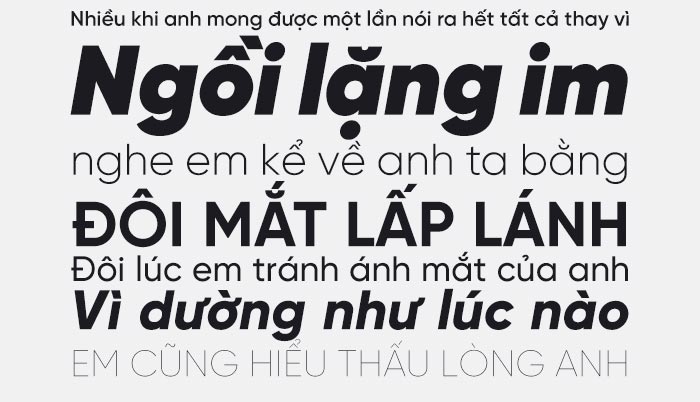
Typeface Serif loại không chân. chúng nhận biết khi chúng ta nhìn ở dưới chân chúng đều không có gạch ngang. Trong khi đó những font khác hay typeface khác đều có những gạch chân. Typeface Serif loại không chân này được rất nhiều người sử dụng để ứng dụng vào thiết kế bảng hiệu. Thiết kế nhanh, kiểu nhìn đẹp và bắt mắt, nét chữ thường tròn và có các kiểu đậm, nhạt, nghiêng, mảnh. Typefaces Serif loại có chân.
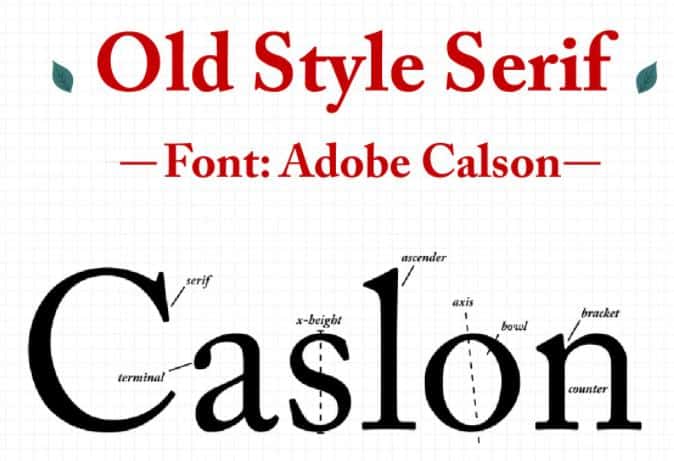
Đọc tiêu đề thì chúng ta đã thấy ngay là Typefaces Serif này là loại có chân. Chúng có gạch ngang ở dưới chân một số chữ cái. Một số nét chữ được xoay nghiêng. Những phần uống lượn nó nhỏ hơn. Các đàu chữ thường có hình nhọn. Transitional serif – loại chuyển tiếp
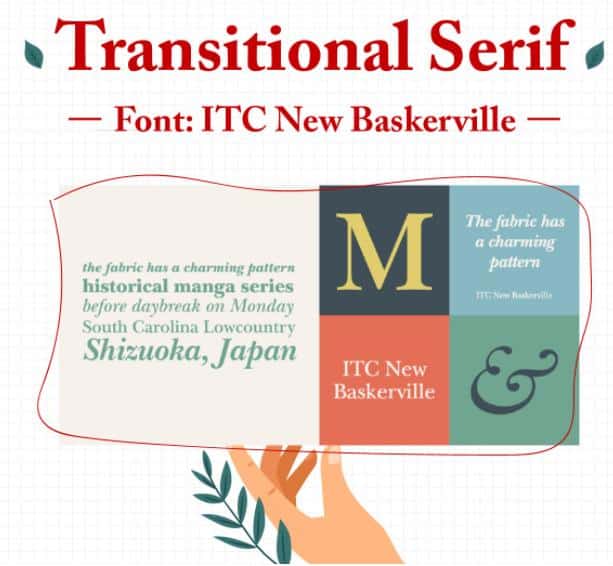
Transitional serif – loại chuyển tiếp là nét chữ vẫn có chân. Các nét chữ của chúng hướng thẳng đứng. Các nét chữ có độ tương phản cao. Geometric Sans loại dạng hình học:
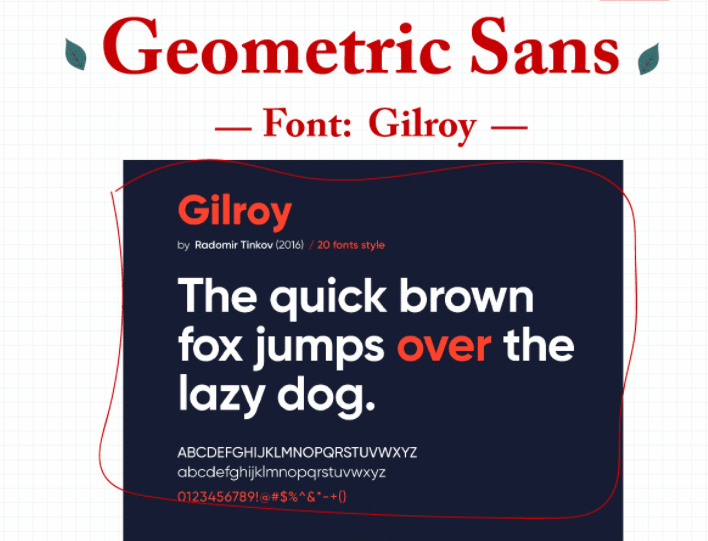
Geometric Sans loại dạng hình học: Là 1 loại chữ không chân các nét chữ tròn đều và nhìn rất đẹp. Phần uốn cong cũng rất đều nhau. Kết thuchs các nét là những nét vuông theo nét chữ.
Một số thuật ngữ trong Typography
Typography được nhiều người biết đến và nó không còn xa lạ với chúng ta. Nhưng đối với 1 số người mới bắt đầu thì đây là một điều mới mẻ. Phần này các bạn sẽ được tìm hiểu một số thuật ngữ trong Typography mà chúng ta hay gặp phải. Thuật ngữ Hierachy trong Typography.
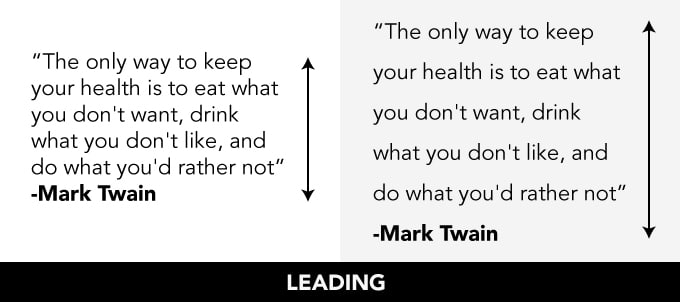
Thuật ngữ này được hướng người đọc đến vị trí quan trọng nhất của hính. Nó được coi là điểm nhấn để thu hút người đọc hơn. Nói cách khác chúng còn có chức năng giãn chữ hoặc tăng hoặc giảm cỡ chữ để chúng nổi bật hơn. Làm cho chúng khác biệt hơn. Điều chỉnh Hierachy như thế nào:
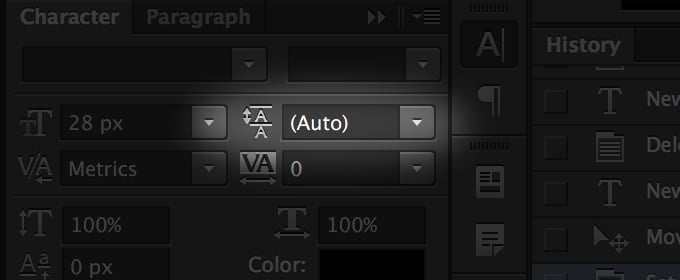
Trên phần mềm các bạn tìm đến cài đặt font chữ và nhìn thấy biểu tượng 2 chữ A chồng lên nhau và có mũi tên là các bạn có thể chỉnh đc cái này. Thuật ngữ Tracking trong Typography.
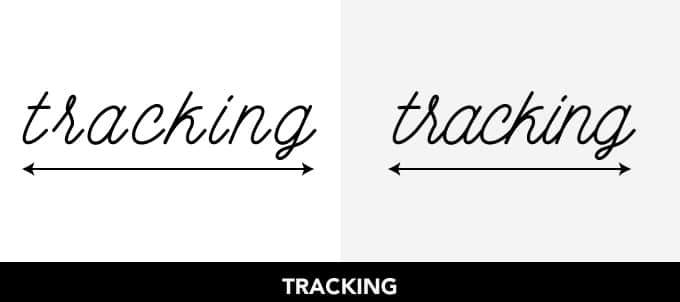
Tracking để được sử dụng để điều chỉnh khoảng cách giữa các chữ với nhau tạo khoảng cách và không gian lớn hơn giữa 2 hay nhiều chữ với nhau sao cho phù hợp nhất. Việc này làm cho một từ đơn lẻ nhìn có vẻ thoáng và ấn tượng hơn. Cách điều chỉnh Tracking
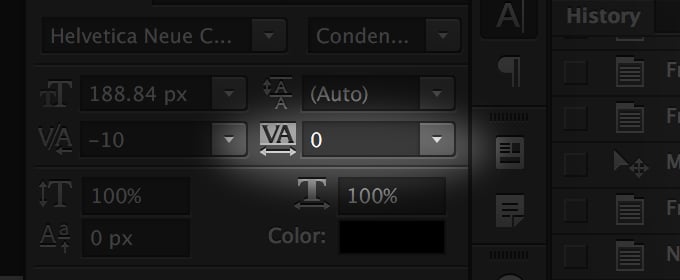
Trên phần mềm các bạn tìm đến cài đặt font chữ và nhìn thấy biểu tượng 2 chữ V và chữ A giáp nhau và có mũi tên đi sang 2 bên là các bạn có thể chỉnh đc cái này. Thuật ngữ Kerning trong Typography.
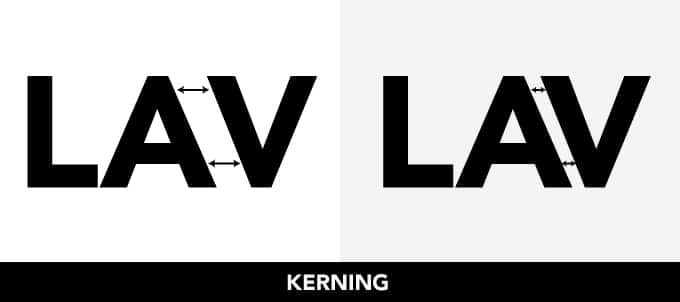
Kerning là khoảng cách giữa 2 chữ cái, 2 số, 2 dấu, hay còn gọi là 2 ký tự liền với nhau. Và điều này làm cho rất hay nhầm với Thuật ngữ Tracking thao tác này sẽ điều chỉnh khoảng trống sao cho dễ đọc hoặc làm nổi 1 ký tự nào trong đoạn chữ đó.
Nhìn vào trong bức hình chúng ta thấy chúng ta cũng có 2 chữ V và chữ A vát chéo nhao nhưng lần này nó chỉ có 1 mũi tên hướng sang trái. Tại đây các bạn có thể điều chỉnh Kerning dễ dàng
Tổng kết:
Trong bài viết này mình vừa chia sẻ cho các bạn biết Typography là gì? Những quy tắc thiết kế font chữ trong typography và những thuật ngữ cơ bản trong typography. Nếu các bạn có gì thắc mắc thì hãy để lại bình luận để cùng trao đổi nhé.